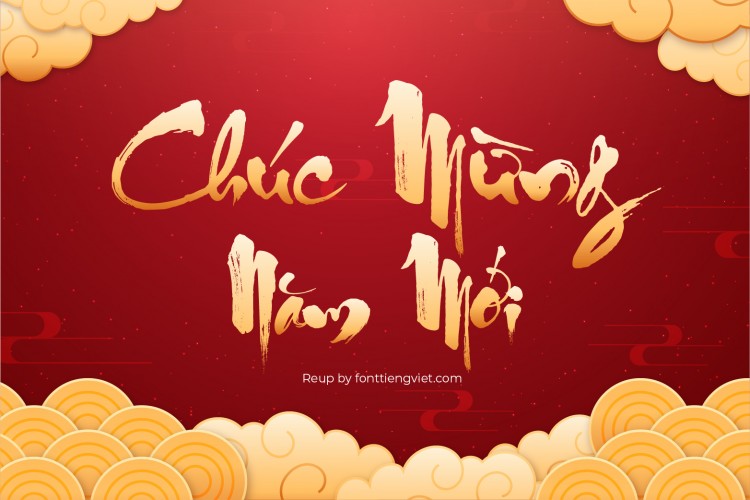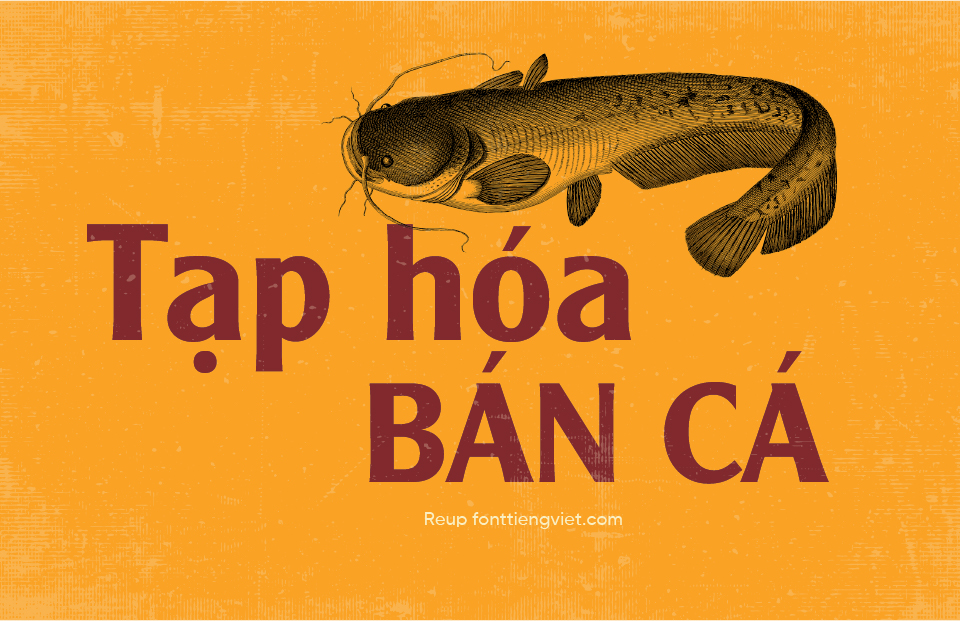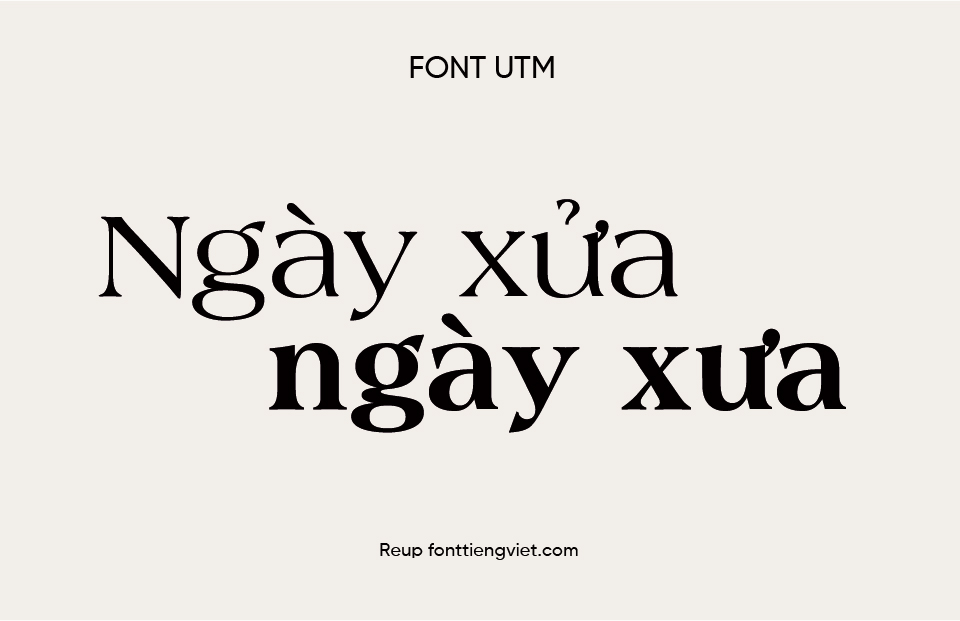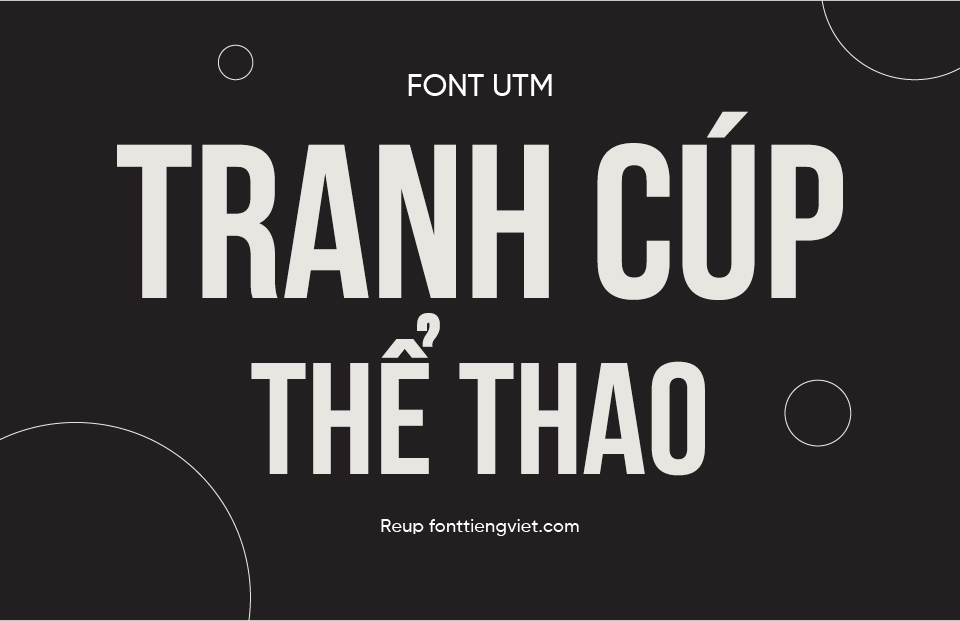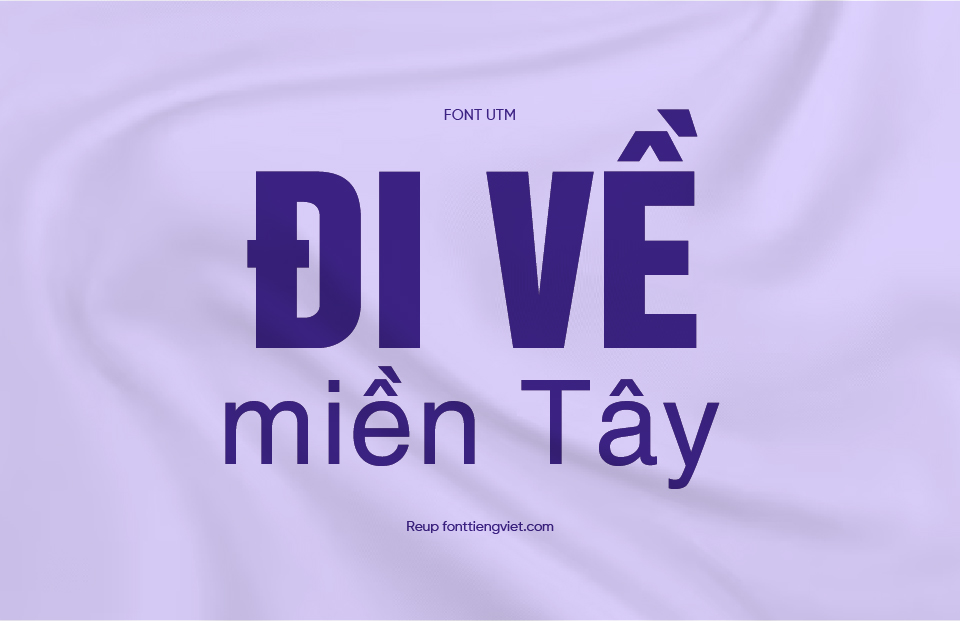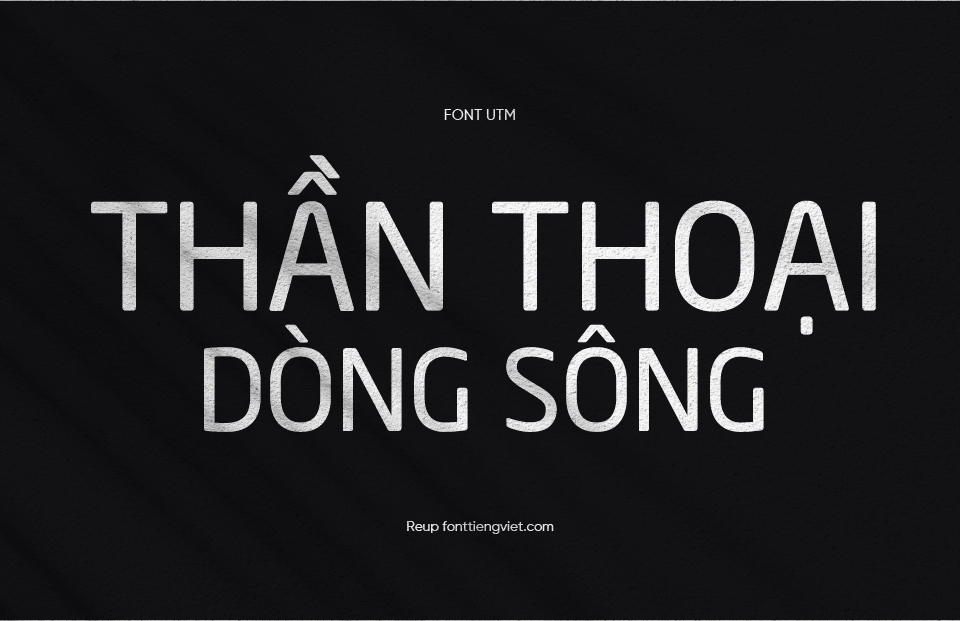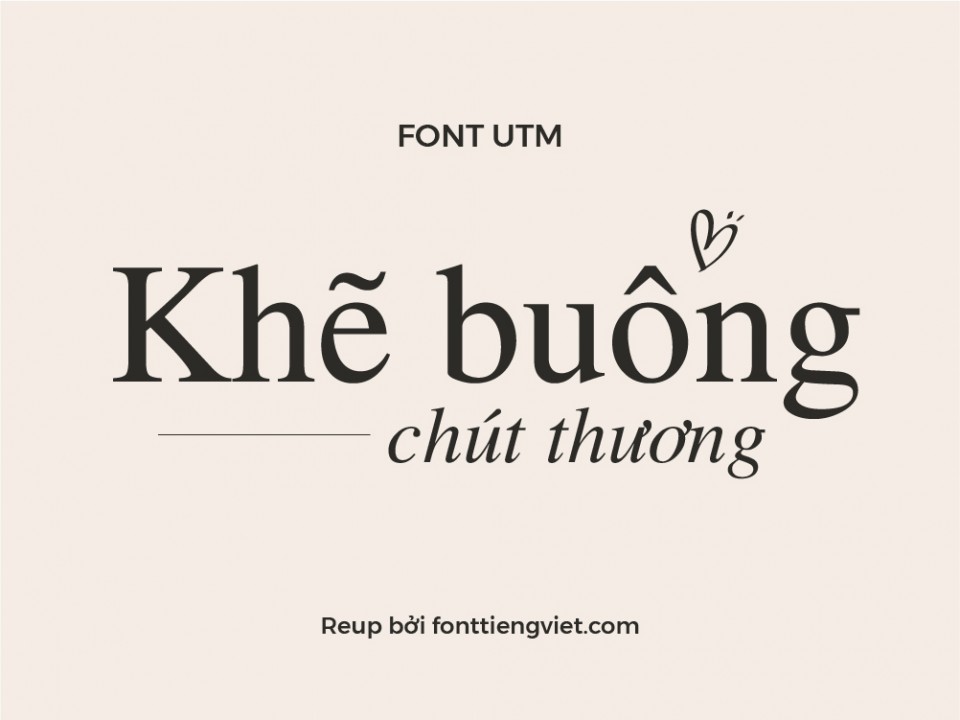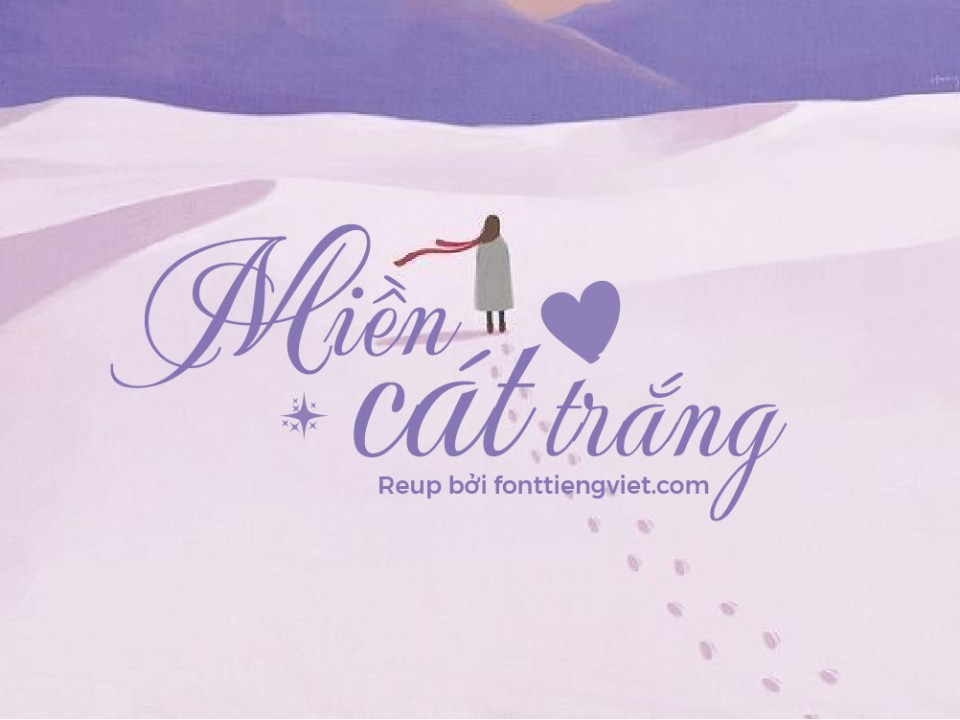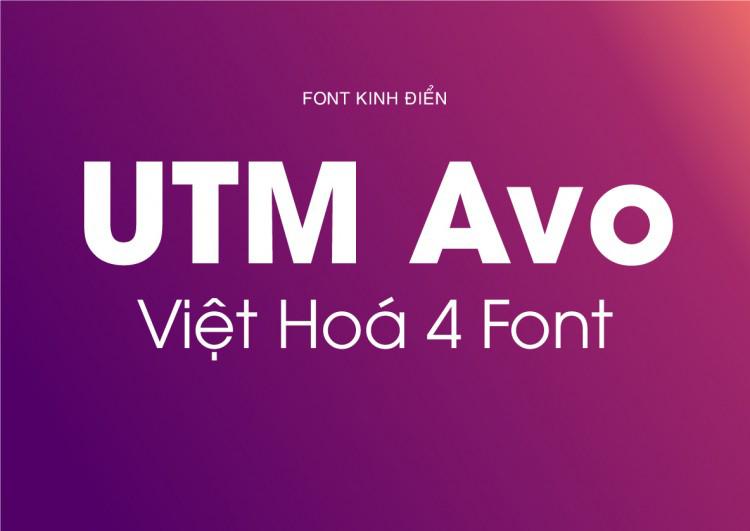
Tổng hợp 100 font UTM đẹp nhất
Font chữ Việt hóa trên Canva là nguồn tài nguyên hữu ích cho các designer. Canva đã tích hợp sẵn rất nhiều font chữ đã được Việt hóa, giúp việc thiết kế trở nên dễ dàng và linh hoạt hơn. Nhờ sự đa dạng về kiểu dáng, người dùng có thể thoải mái sáng tạo để tạo ra những thiết kế đẹp mắt. Dưới đây là tổng hợp một 100 mẫu font Việt hóa trên Canva đẹp nhất.
Font UTM là gì?
Font UTM là một bộ font chữ Việt hóa nổi tiếng được phát triển bởi Công ty Urban Typography Management (UTM) – một đơn vị chuyên thiết kế và phân phối font chữ tại Việt Nam. Bộ font này bao gồm hàng trăm kiểu chữ khác nhau, từ hiện đại, cổ điển đến nghệ thuật, với điểm chung là đều hỗ trợ tiếng Việt đầy đủ, hiển thị rõ ràng và dễ đọc.
Điểm đặc biệt của font UTM là toàn bộ các ký tự tiếng Việt, bao gồm dấu, chữ hoa, chữ thường, ký tự đặc biệt… đều được thiết kế chỉn chu, cân đối và hài hòa, đảm bảo tính thẩm mỹ cao trong mọi ấn phẩm, từ in ấn cho đến thiết kế kỹ thuật số.
Lợi ích khi sử dụng font UTM trong thiết kế
Font UTM không chỉ phổ biến mà còn được đánh giá cao bởi cộng đồng thiết kế trong và ngoài nước nhờ vào những ưu điểm nổi bật sau:
Việt hóa hoàn chỉnh: Tất cả các font trong bộ UTM đều được thiết kế với bảng mã Unicode đầy đủ, hỗ trợ tiếng Việt 100%, không lỗi dấu, không lỗi hiển thị, tương thích với mọi phần mềm xử lý văn bản và thiết kế đồ họa.
Đa dạng phong cách thiết kế: Bộ font UTM bao gồm nhiều thể loại chữ khác nhau như sans-serif (chữ không chân), serif (chữ có chân), handwriting (chữ viết tay), calligraphy (chữ nghệ thuật), display (chữ trang trí)… phù hợp với nhiều mục đích sử dụng như thiết kế banner, poster, logo, thiệp mời, tài liệu học tập, trình chiếu PowerPoint…
Tương thích cao: Font hoạt động tốt trên mọi hệ điều hành (Windows, macOS, Linux…) và có thể sử dụng trực tiếp trên các phần mềm như Microsoft Word, Excel, PowerPoint, Photoshop, Illustrator, CorelDRAW và các công cụ thiết kế online như Canva (nếu sử dụng bản Pro).
Một số font nổi bật trong bộ UTM
Dưới đây là một số font tiêu biểu trong bộ font UTM mà bạn có thể sử dụng ngay sau khi cài đặt:
UTM Avo / AvoBold: Font sans-serif hiện đại, gọn gàng, dễ đọc, rất phù hợp để làm tiêu đề, slide thuyết trình hoặc thiết kế web. Phiên bản Bold tạo điểm nhấn mạnh mẽ hơn.
UTM Avo / AvoBold
UTM Helve / HelveBold: Lấy cảm hứng từ Helvetica, font chữ này tạo cảm giác chuyên nghiệp, cân đối, rõ ràng. Thích hợp dùng trong thiết kế thương hiệu, logo hoặc tài liệu kỹ thuật.
UTM Helve / HelveBold
UTM Neo Sans: Phong cách bo tròn mềm mại, tạo cảm giác thân thiện và trẻ trung. Rất phù hợp với các sản phẩm dành cho học sinh, trẻ em hoặc thiết kế giáo dục.
UTM Neo Sans
UTM Times: Biến thể Việt hóa của Times New Roman, trình bày văn bản rất chuẩn và đẹp mắt. Phù hợp cho các tài liệu văn phòng, báo chí, tiểu luận học thuật.
UTM Times
UTM Americana: Font serif cổ điển, nét chữ mềm mại nhưng vẫn trang trọng. Rất thích hợp dùng cho tiêu đề trang trọng, thư mời, hoặc văn bản mang tính hoài niệm.
UTM Americana
UTM Alexander: Chữ viết tay nghệ thuật, mềm mại và bay bổng, tạo cảm giác tinh tế. Thường dùng cho thiệp mời, tiêu đề nghệ thuật hoặc lời chúc.
UTM Alexander
UTM ThuPhap Thien An: Font thư pháp độc đáo, đậm chất Á Đông, phù hợp cho các thiết kế dịp Tết, tranh chữ thư pháp, hoặc các thiết kế mang tính truyền thống.
UTM ThuPhap Thien An
UTM Wedding K&T: Chữ viết tay hiện đại, lãng mạn, rất phù hợp cho các thiết kế cưới, lời mời, bìa album ảnh hoặc các sản phẩm mang hơi hướng tình cảm.
UTM Wedding K&T
UTM Bebas: Chữ in hoa mạnh mẽ, phù hợp cho các tiêu đề nổi bật, poster quảng cáo hoặc banner sản phẩm. Đơn giản nhưng gây ấn tượng thị giác cao.
UTM Bebas
Kết luận
Bộ font UTM là nguồn tài nguyên font chữ Việt hóa chất lượng cao, phù hợp với nhiều phong cách thiết kế khác nhau. Dù bạn là học sinh, giáo viên, nhân viên văn phòng hay designer chuyên nghiệp, thì font UTM đều có thể đáp ứng tốt nhu cầu trình bày văn bản, thiết kế đồ họa và sáng tạo nội dung của bạn.